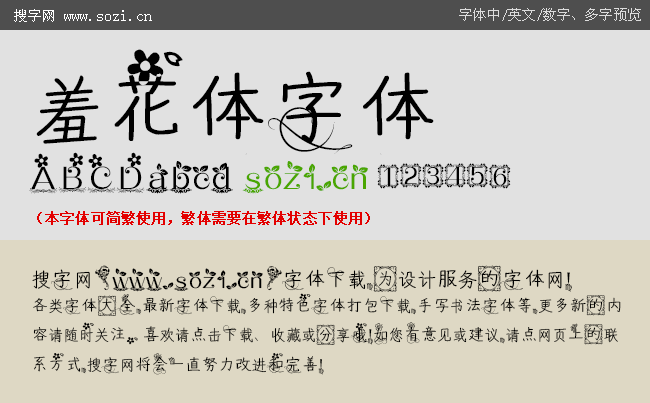
羞花體字體
搜字網(wǎng)給大家提供一款很帶有手寫風(fēng)格的卡通手機(jī)中文字體下載。修改者將它命名為羞花體字體,這款手機(jī)字體是在仿照兒童手寫風(fēng)格的卡通手寫字體筆畫間加上卡通圖案。即有卡通字體的趣味性,又有手寫字體的藝術(shù)性,真是童趣十足的一款字體,特別適合喜歡手機(jī)字體個(gè)性一些的朋友在手機(jī)上安裝使用。